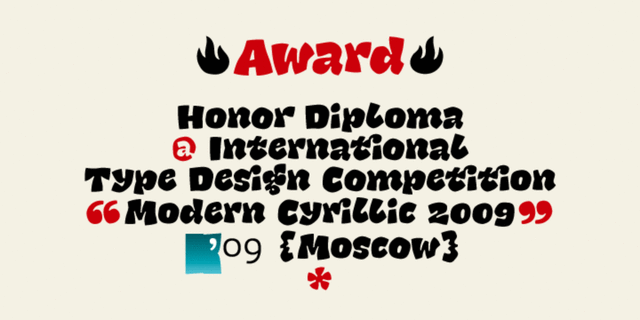
Шрифт Крокодила был разработан Дмитрием Растворцевым в 2009 году по просьбе издательства «Микко». Нужен был прикольный детский шрифт с кириллицей для обложки, а таких шрифтов до сих пор очень мало.
веселый, тяжелый, заметный, броский, тесный, громкий, задорный, смешной, прыгающий, неряшливый, игривый, озорной, непоседливый, подвижный, оригинальный, динамичный, спелый, вкусный, жеваный, детский, наивный, карикатурный, зубастый, мультяшный, звериный, жаркий, южный, прикольный, дикий, задиристый, сумасбродный, живой, непослушный, грубый, характерный, неотесанный, неровный, праздный, гуляющий, балованный, сильный, прожорливый, яркий, активный, остроумный, летний, тропический, небрежный
детская книжка, лагерь, юмор, анимация, завтрак, игрушка, еда, закуска, аттракцион, цирк, зоопарк, специи, раскраска, хенд мейд, игра, зоомагазин, животные, отдых, мультфильм, школа, каникулы, перец, графика, иллюстрация Стилистика: